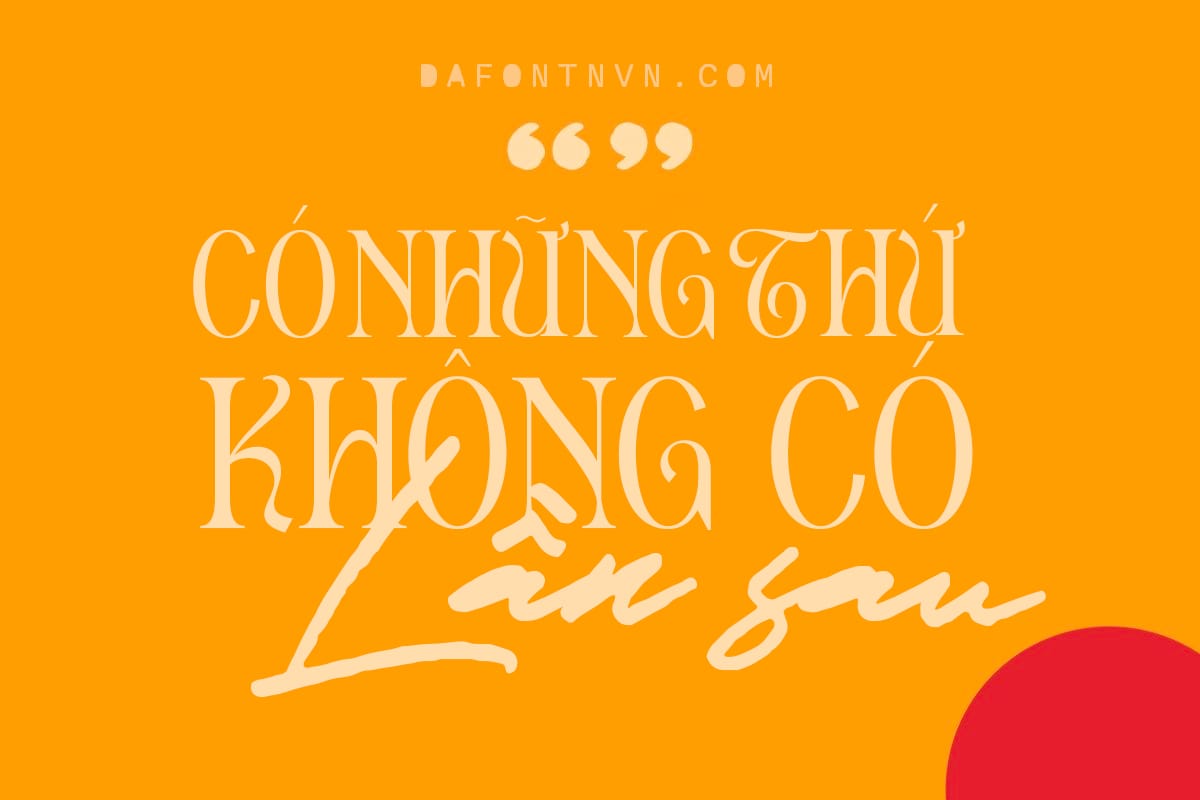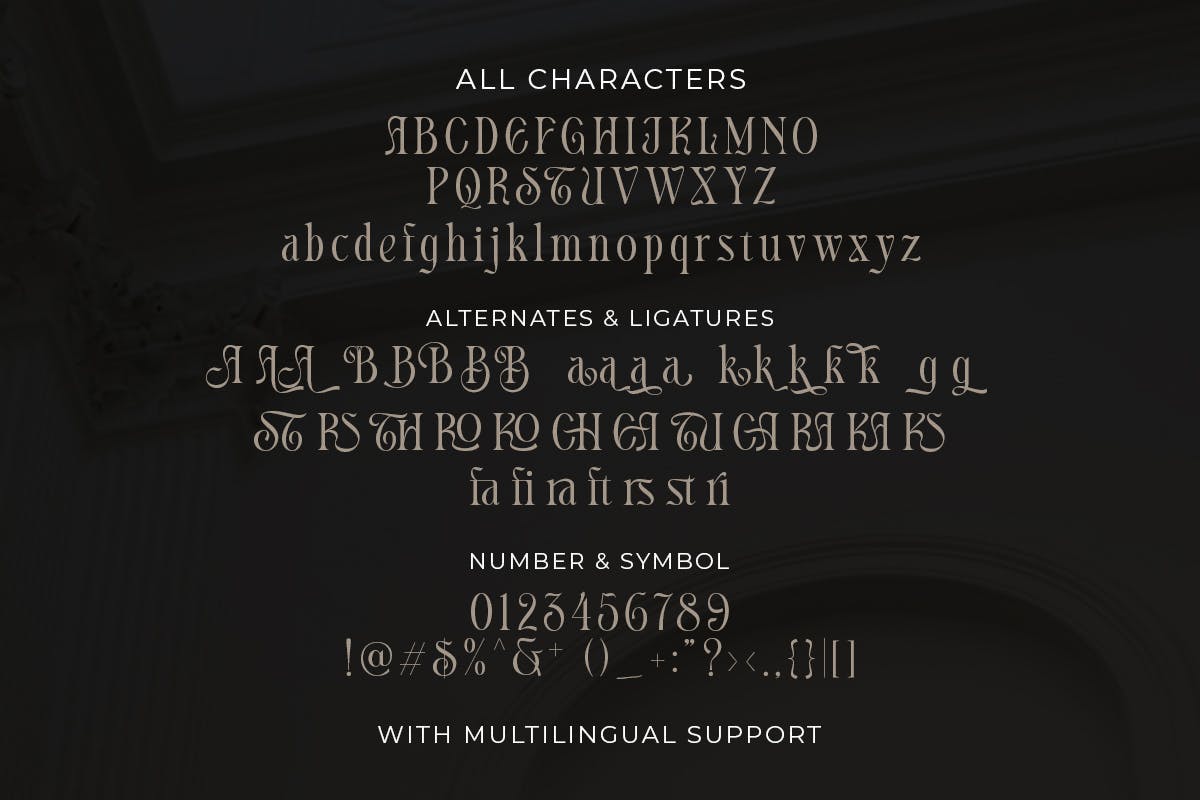
Font Appears là một kiểu phông chữ hiện đại, tối giản mang phong cách gọn gàng và kiểu dáng đẹp. Xen kẽ phong cách và chữ ghép làm cho phông chữ trở nên độc đáo hơn và nổi bật trong các thiết kế.
Font Appears việt hóa phù hợp với các thiết kế khác nhau như thiệp mời, nhãn, biểu trương, tạp chí, bao bì, thời trang, typography, quảng cáo… Ngoài ra font đi kèm với rất nhiều Glyph khác nhau để bạn có thể áp dụng và tạo ra thiết kế ấn tượng cho riêng mình.